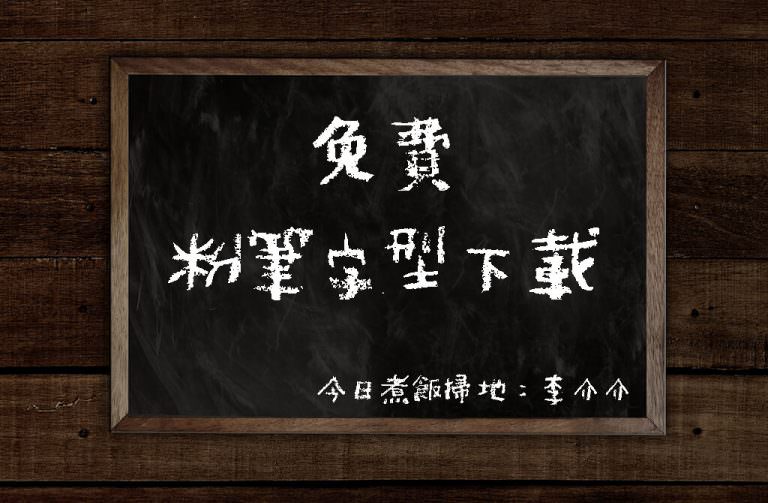
免費字體手寫風格的蠟筆字型下載,像黑板上的粉筆字
這款字體是 Do-Font 設計以模仿蠟筆手寫的風格,名子叫做 Strike Crayon,其實樣式也蠻像黑板上的粉筆字,都帶有濃濃的手寫風格,這款字體可以用在商業用途上使用,但不可以販售該字體
另外這個字體我覺得用在英文上辨識上可能沒有那麼好,例如像是英文大寫的 G 長得很像數字的 4(上圖) ,所以建議用其他的英文字體取代會比較適合